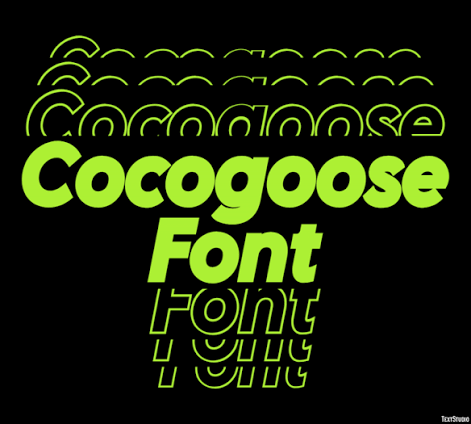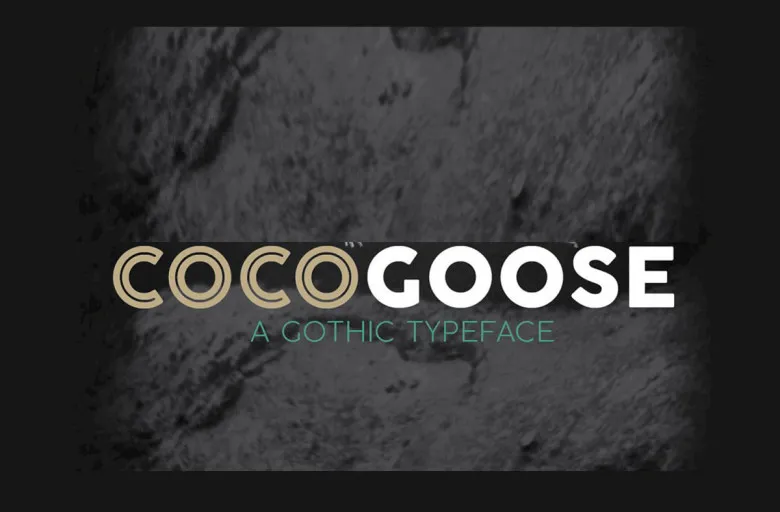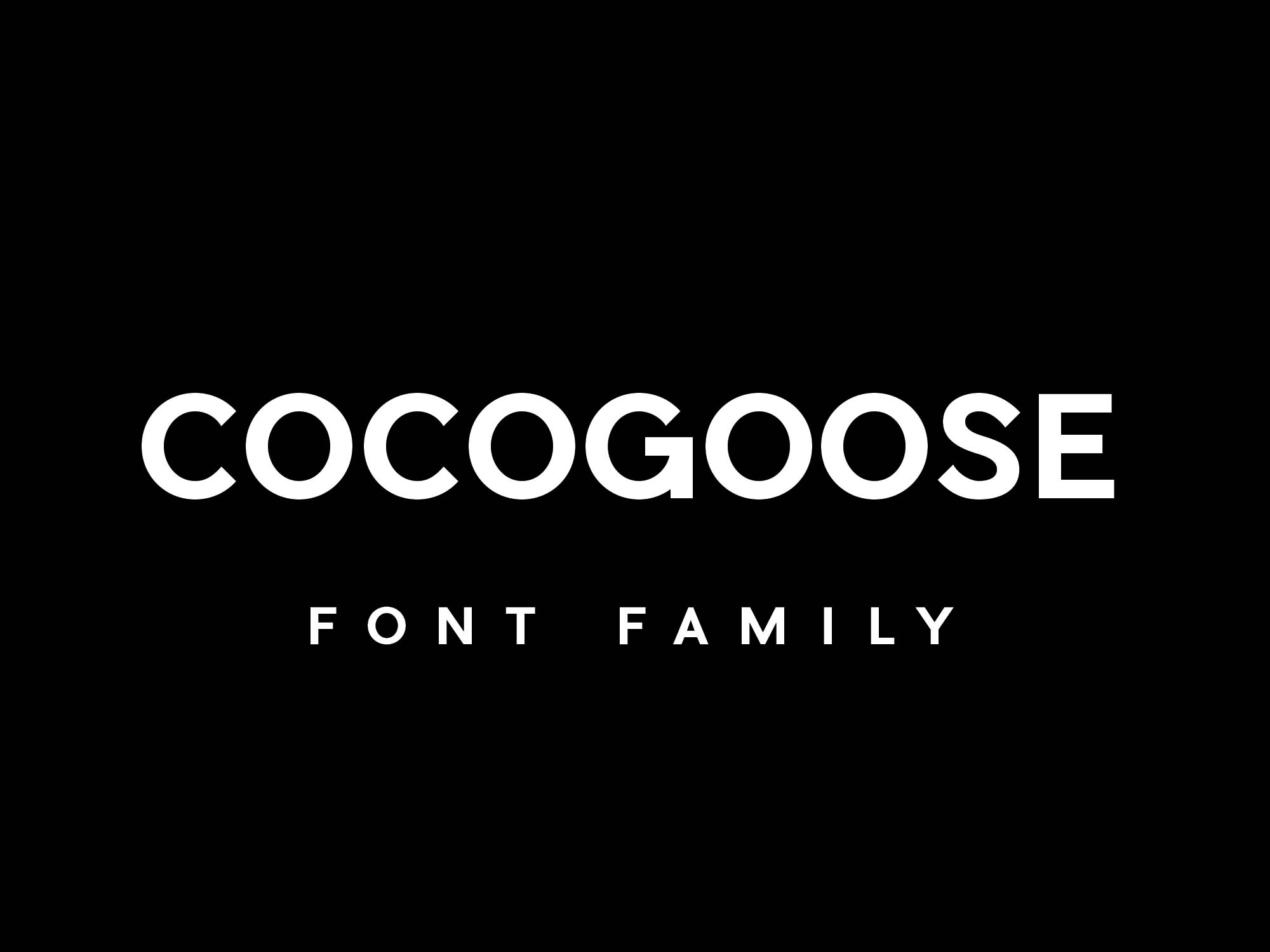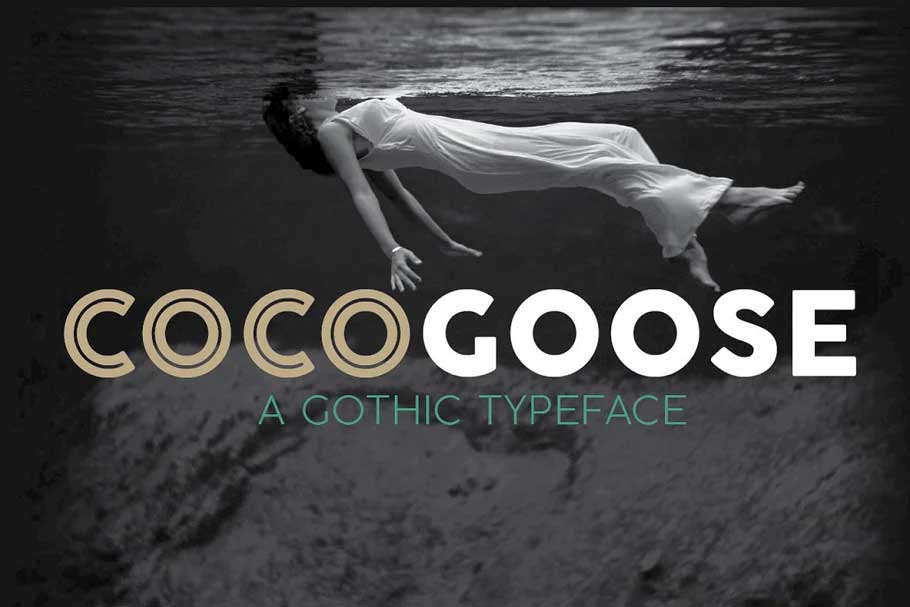
Cocogoose Font Việt hóa là bộ phông chữ không chân (Geometric Sans-serif) hiện đại mang phong cách hình học tròn trịa, vững chãi và tràn đầy năng lượng thị giác, được sáng tạo bởi nhà thiết kế Cosimo Lorenzo Pancini thuộc xưởng đúc chữ danh tiếng Zetafonts. Với cấu trúc nét chữ dày dặn, các đường bo góc tinh tế và tính nhận diện vượt trội, Cocogoose là lựa chọn hoàn mỹ cho các thiết kế logo startup công nghệ, bao bì thực phẩm sạch, túi giấy thời trang đường phố và ấn phẩm sự kiện sáng tạo. Doozypack.vn cung cấp link tải font Cocogoose Việt hóa chuẩn kỹ thuật, giúp bạn sở hữu phông chữ đẳng cấp mà không lo gặp bất kỳ lỗi hiển thị dấu thanh nào khi thiết kế in ấn.
Đặc điểm thẩm mỹ độc đáo của Cocogoose Font
Cocogoose được lấy cảm hứng từ cấu trúc hình học chuẩn mực của trường phái Bauhaus kết hợp cùng nhịp điệu đồ họa hiện đại của thế kỷ 21, mang lại vẻ ngoài trẻ trung nhưng vô cùng chững chạc.
Cấu trúc Geometric Sans-serif vững chãi và hiện đại
Đặc trưng lớn nhất của Cocogoose Font Việt hóa là các con chữ được xây dựng dựa trên những khối hình học cơ bản như hình tròn và đường thẳng dứt khoát. Thân chữ thẳng đứng kiêu hãnh, tỷ lệ x-height lớn tạo ra một sức nặng thị giác ấn tượng, giúp tiêu đề bản thiết kế của bạn ngay lập tức thu hút ánh nhìn từ khoảng cách xa. Phong cách này toát lên sự minh bạch, uy tín và chuyên nghiệp, rất phù hợp với các thương hiệu muốn khẳng định sự bền vững và tiên phong trên thị trường.
Đường nét bo tròn nhẹ nhàng mang lại sự thân thiện
Khác với các dòng phông chữ hình học góc cạnh sắc nhọn, Cocogoose sở hữu các góc bo nhẹ nhàng ở các điểm giao nét. Chi tiết này giúp làm mềm đi sự khô cứng công nghiệp, mang lại cảm giác ấm áp, gần gũi và dễ tiếp cận cho người tiêu dùng, cực kỳ ăn ý với các sản phẩm tiêu dùng nhanh, đồ uống giải khát hoặc các dòng mỹ phẩm chăm sóc sức khỏe gia đình.
03 Ưu điểm nổi bật của bản Cocogoose Font Việt hóa
Khi ứng dụng các phông chữ hình học quốc tế vào thị trường trong nước, sự chỉn chu về dấu câu là yếu tố quyết định đến tính chuyên nghiệp của bản thiết kế:
- Khắc phục triệt để lỗi dấu tiếng Việt: Phiên bản Việt hóa đã được đội ngũ thiết kế trau chuốt thủ công từng dấu câu. Các dấu sắc, huyền, hỏi, ngã, nặng được vẽ với tỷ lệ cân đối, bo nhẹ đồng điệu cùng thân chữ gốc, không gây cảm giác chắp vá hay đè nét làm mất tính thẩm mỹ.
- Bảo đảm tính đồng nhất thương hiệu: Việc tải font Việt hóa Cocogoose chuẩn giúp bạn tự tin dàn trang tiêu đề tiếng Việt mà không lo hiện tượng lỗi ô vuông hay nhảy về font hệ thống khô khan.
- Kiểm soát hiện tượng tràn mực (Dot Gain) tại khe chữ nhỏ: Các khoảng hở bên trong chữ cái (như chữ ‘e’, ‘a’, ‘o’) khá nhỏ ở biến thể Bold. Khi in trên giấy Kraft hút mực nhanh, mực có thể bị lan làm bít kín các lỗ hở này. Bạn nên giữ size chữ tiêu đề tối thiểu từ 9pt trở lên để bảo đảm độ sắc nét.